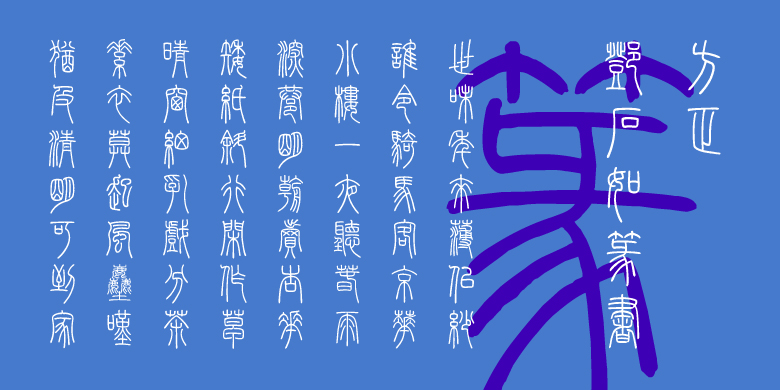
方正鄧石如篆書
常规书写·毛笔
方正邓石如篆书 字体对比
关于邓石如:
邓石如(1743-1805年),安徽怀宁人,原名琰,字石如,号顽伯,完白山人,因避清仁宗名讳,故以字行。
邓石如为清代碑学书家巨擘,擅长四体书,其书法艺术是我国书法史上一座杰出的丰碑。他是真正的碑学实践范例,他的出现,标志着碑学派已经创造出自己的碑派面目。他以隶法作篆,突破了千年来玉筯篆的樊篱,富有创造性地将隶书笔法糅合其中,大胆地用长锋软毫,提按起伏,极大丰富了篆书的用笔,特别是晚年的篆书,线条圆涩厚重,雄浑苍茫,臻于化境,开创了清人篆书的典型,对篆书一艺的发展作出不朽贡献。
字体特征:
方正邓石如篆书以邓石如《四体书册之篆书八闼册》(又称《篆书格言册》)的书法特点为基础临创开发,字体既婉转流畅又刚健朴拙。